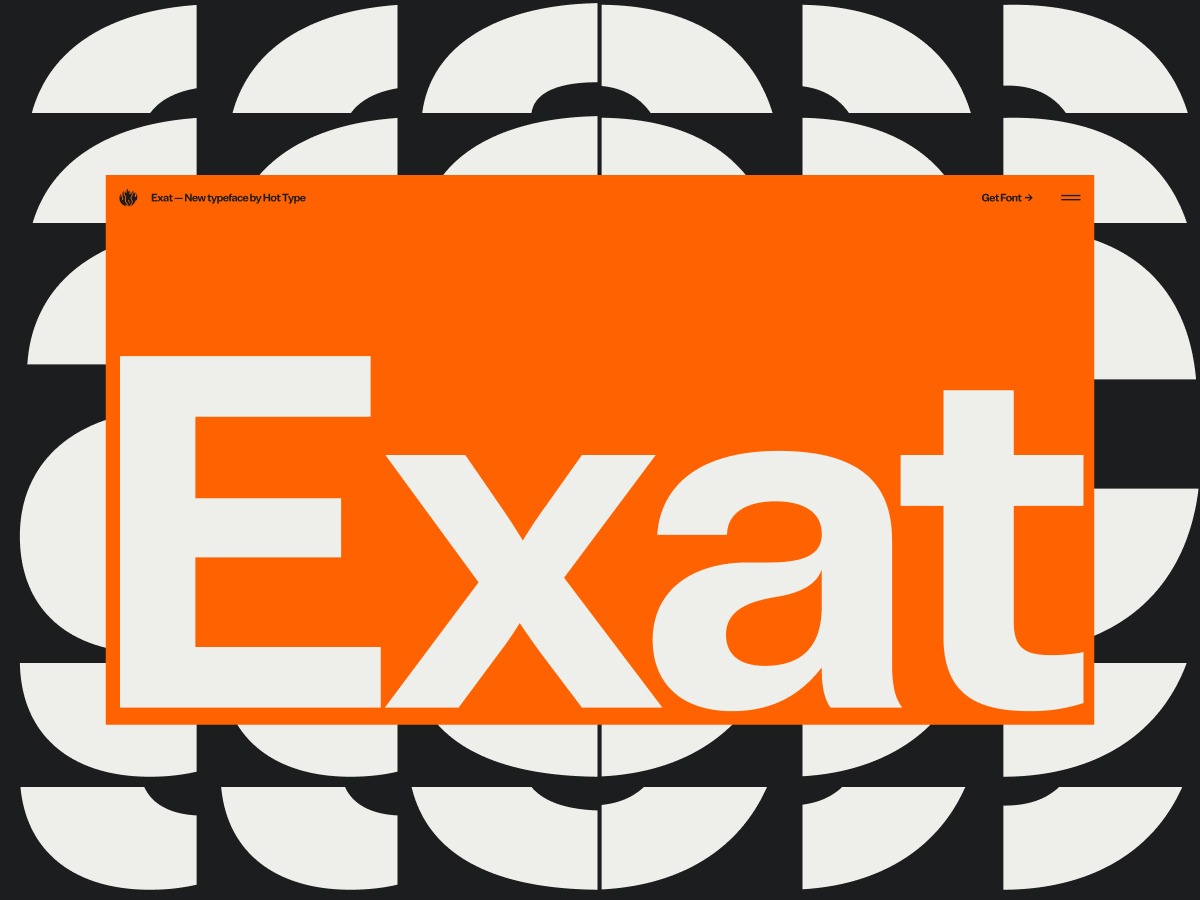
El micrositio de fuentes variables Exat redefine la tipografía como un sistema vivo
El micrositio de fuentes variables Exat de Studio Size transforma las 21 fuentes de Hot Type en pantallas tipográficas interactivas activadas por desplazamiento y reactivas al cursor.
Exat de Hot Type es uno de los lanzamientos tipográficos más ambiciosos de 2026. Inspirada en el colectivo modernista croata EXAT 51, la fuente variable Exat abarca subfamilias comprimidas, normales y anchas de siete pesos, con 1.715 glifos que cubren escrituras latinas y cirílicas. Tipos populares de preguntas Tamaño del estudio Cree un sitio web promocional acorde con ese alcance.
El resultado ve la tipografía como un comportamiento más que como una decoración. Cada sección introduce un eje del sistema de tipos, luego avanza y luego se vuelve repetitivo. El desplazamiento impulsa la estructura directamente: la posición es igual al estado, no al orden, por lo que la inversión restaura la forma anterior. Las secciones de lectura tranquila se reemplazan por secciones expresivas más intensivas, lo que controla la fatiga visual y muestra el alcance completo del sistema.
Cómo responden las fuentes variables Exat a las interacciones
La cuadrícula de glifos activada es la visualización más directa del micrositio. El campo de caracteres en minúscula reacciona a la posición del cursor, cambiando de grosor y color a través de siete anillos concéntricos de influencia. El anillo más externo hace que los caracteres sean de color azul oscuro con un peso mínimo. El anillo más cercano los dispara en rojo con el peso máximo. No hay ningún título que explique esto. El comportamiento se lee inmediatamente.
La sección de espacio de diseño maneja comparaciones controladas: al pasar el cursor sobre el nombre de un estilo, el texto de muestra cambia instantáneamente entre peso y ancho. Los números grandes se mueven en un patrón de onda sinusoidal relacionado con la velocidad de desplazamiento, agregando profundidad temporal sin competir con la fuente. La presentación tridimensional pone poco énfasis en la experiencia, haciendo referencia al espíritu geométrico de EXAT 51 sin abrumar la página.